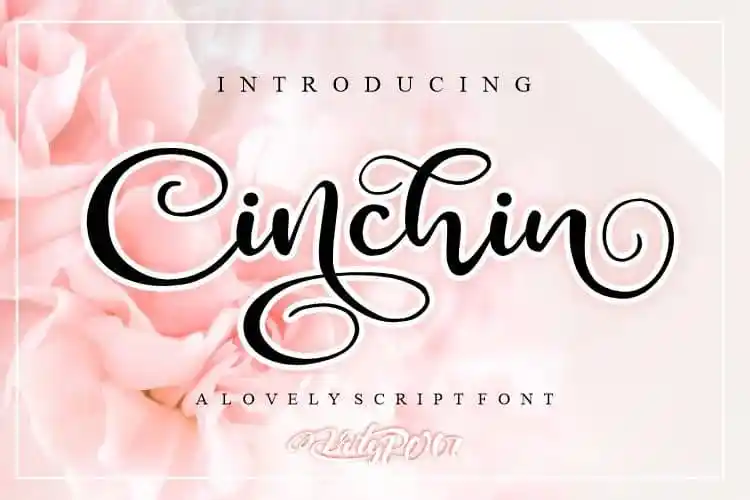
Cinchin Calligraphy Font – Download Grátis
A Cinchin Calligraphy Font é uma bela fonte de script criada pelo designer artype07. Esta fonte moderna, feita à mão, oferece uma aparição autêntica que mistura a elegância do caligrafismo com a frescura dos traços humanos. O design inclui 3 letras maiúsculas alternativas, contendo desenhos chamativos e swashes para um toque de personalidade. Além disso, oferece caracteres alternativos com detalhes adoráveis e a ligação de letras única, que tornam esta fonte perfeita para aplicar em materiais gráficos como cartazes, selos ou editoriais. Como se não bastasse, a Cinchin Calligraphy Font suporta múltiplas línguas, o que aumenta ainda mais sua versatilidade e conveniência. Com um rápido acesso por meio do mapa de caracteres, da Biblioteca de Fontes, ou usando seu programa de gerenciamento de fontes favorito, qualquer usuário pode explorar as infinitas possibilidades criativas desta fonte.